现今,字体作为重要的视觉语言而被越来越多的设计师所关注,而在实际设计作品输出当中,字体也扮演着将产品理念传递给用户的媒介角色。可见,完整的设计作品是离不开文字的造型表现的,那么,了解字体设计趋势也显得尤为重要。
1. 几何无衬线字体
几何无衬线字依然在运营设计中是首选字体,因为它具有易读性和可接近性特点,以及潮流干练的视觉风格。几何无衬线字体不仅为产品提供了相对中立的容器来传递信息,而且还可以轻松地跨不同应用平台进行转换。
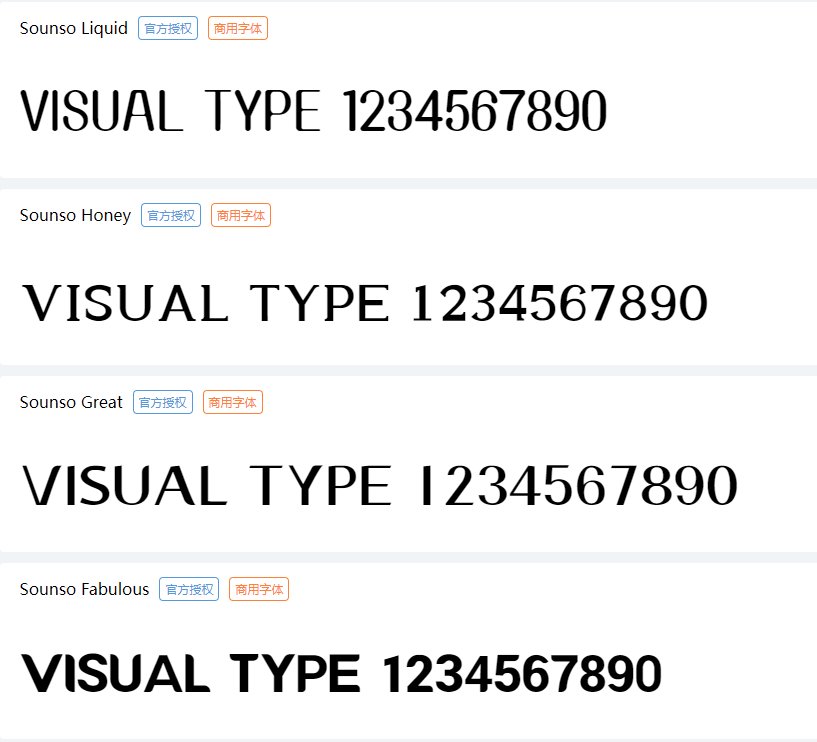
2. 字体图形化
用字体绘制各种不同的形状正成为字体设计的另一大趋势。其表现手法非常多样化,比如字体旋转、圆环、连环曲线等;或者将文字组成立方体、楼梯等具象实物。这些图形化的核心就是在二维的静态画面上,演绎三维对象,从而让版面「静中有动」,增加趣味和动感,突出视觉效果。
3. 动态字体
当静态文字无法满足对主题的诠释,吸引用户眼球时,添加动效会让平淡的画面炫动起来,这无疑为字体带来更多的创意空间,以及更多的设计可行性。